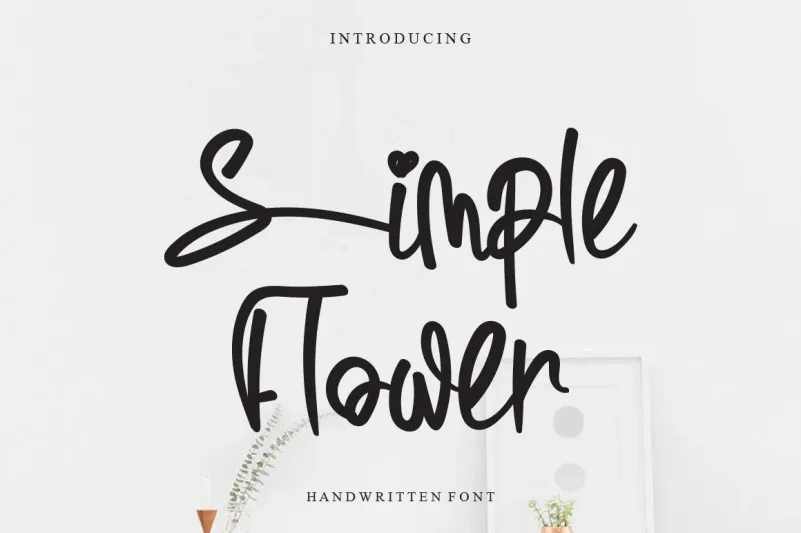
A fonte ‘Simple Flower Font’ do designer LevinCreative é uma escrita flutuante com um tema descontraído que destaca um estilo agradável e leve. Ideal para qualquer projeto, seja ele editorial, gráficos ou criações digitais, esta font se destaca como uma peça única em seu acervo de fontes. Seja você designer ou grafista, essa fonte tem o potencial de transformar sua arte em algo realmente especial. Envolventemente simples e agradável para usar, ela oferece um toque delicado que certamente enriquecerá qualquer projeto. Não hesite em explorar os limites criativos com esta mão-drita única.